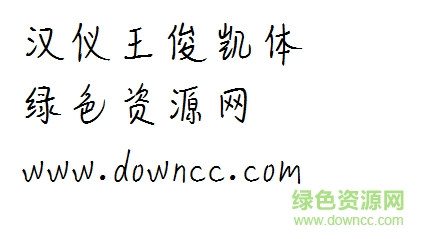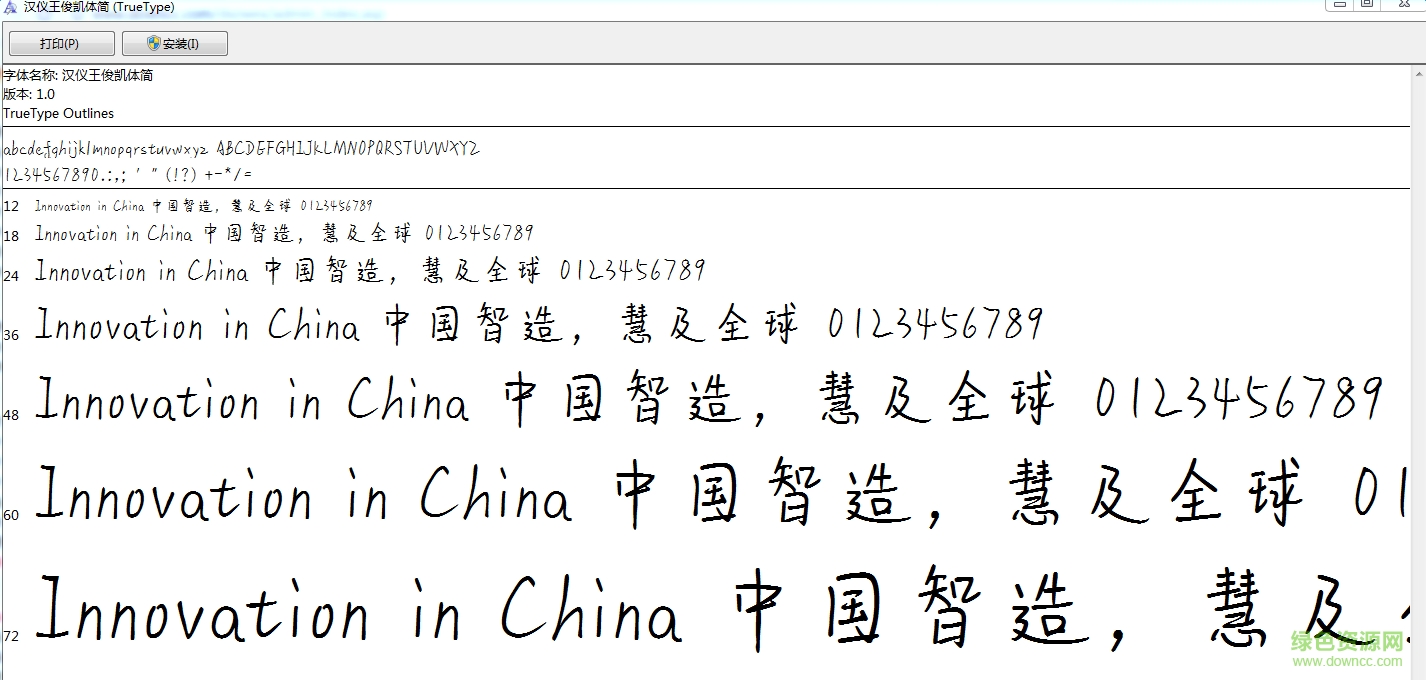
漢儀王俊凱字體是一款漢儀類王俊凱字體軟件,王俊凱的字體給人非常舒服的感覺,深受廣大年輕人的喜愛,更是00后童鞋心目中的偶像字體,還有更多好看字體盡情期待,歡迎到綠色資源網(wǎng)下載體驗(yàn)!
王俊凱的字曝光后,清秀、小巧的字體得到好評(píng)。就在近日,其字體被漢儀字庫(kù)收錄。在王俊凱以往詮釋的角色中,少男氣十足,小編此次給大家?guī)淼氖菨h儀王俊凱字體。